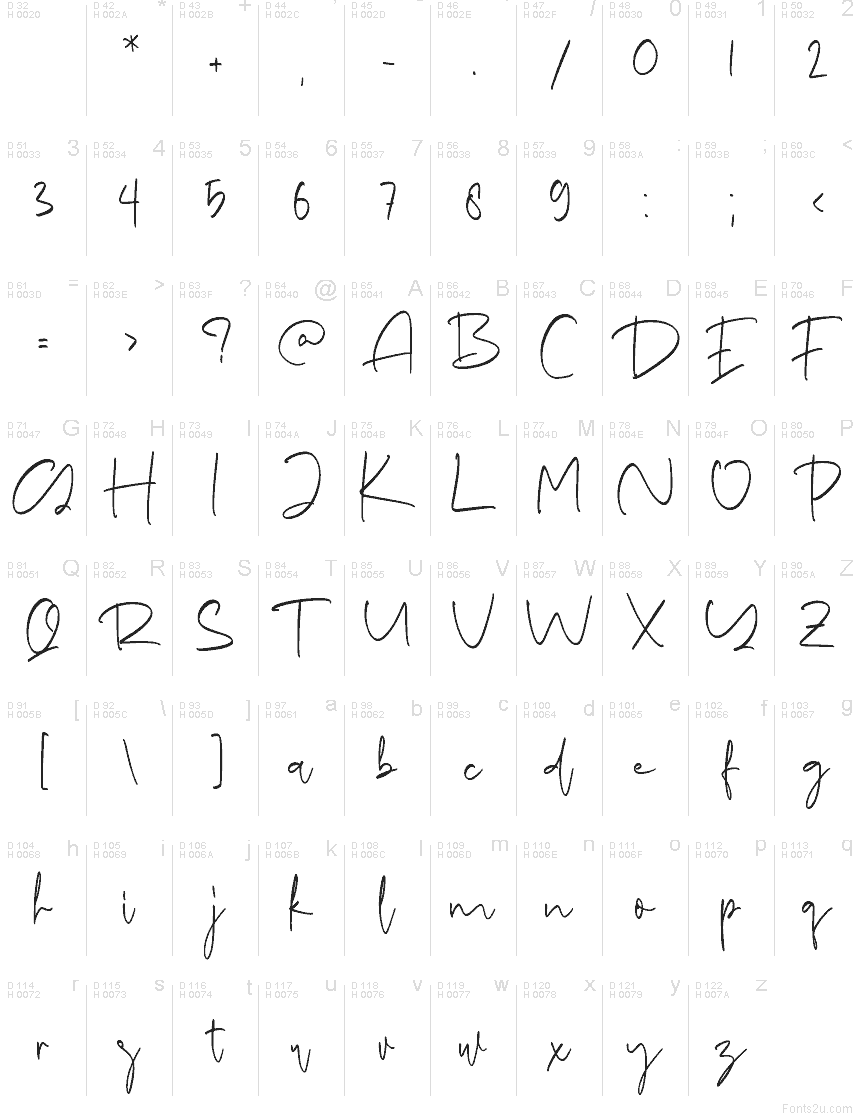
Resetta Milestone
Resetta Milestoneは、なめらかな紙の上をインクが走るような、軽やかで抜け感のある表情を持つ無料の手書きシグネチャーフォントです。縦長でのびやかな文字、細めのストローク、力みのないカーブによって、さっと書いた本物のサインのような印象に。上品でありながら、堅すぎたり作り込みすぎたりしないのも魅力です。線のわずかな揺らぎやかすかな質感が、親しみやすさと人の手の温度をしっかり残しています。
Resetta Milestoneフォントを使うと、テキストがまるで作品にそっと添えた私的なメッセージのように見えます。ロゴ、署名風のウォーターマーク、SNS投稿、ウェディングペーパーアイテム、ブログヘッダー、商品パッケージ、ライフスタイル系の引用文にぴったりです。この無料フォントは大きめに使い、余白をしっかり取ることでいっそう映えます。本文にはクリーンなサンセリフ体を合わせると、洗練された印象と読みやすさを両立できます。